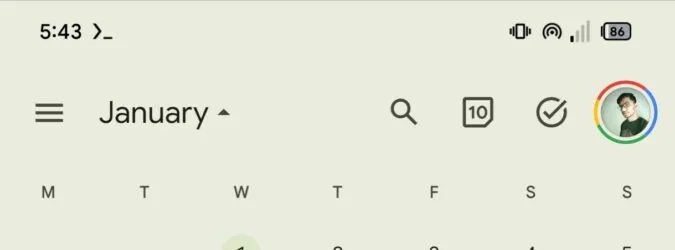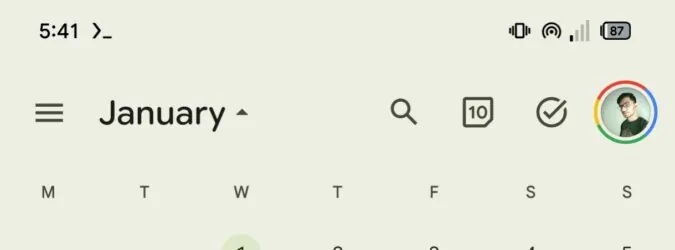
Google lavora per apportare alcune modifiche a Google Calendar, l’app calendario predefinita sui dispositivi della gamma Pixel e su altri dispositivi Android di produttori che non offrono una propria alternativa.
Nello specifico, il team di sviluppo vuole dotare l’app di una nuova impostazione per impedire la condivisione delle informazioni con altre app di calendario. Sembra, inoltre, che presto potrebbe arrivare un piccolo cambiamento allo stile dei caratteri interni all’app.
Due novità in arrivo su Google Calendar
Google Calendar è una di quelle app targate Google che non offre un programma beta pubblico, rendendo più difficile (ma non impossibile) agli insider scovare le funzionalità che verranno implementate in futuro.
Analizzando a fondo la recente versione 2025.10.0-735189449-release dell’app, il solito AssembleDebug (via AndroidAuthority) ha scovato un paio di cambiamenti a cui il team di sviluppo sta lavorando e che potrebbero vedere la luce con un futuro aggiornamento dell’app (o tramite un rilascio lato server).
Nuova impostazione per bloccare l’accesso alle informazioni del calendario
Attualmente, quando un utente concede i permessi per accedere al calendario, l’app sfrutta l’API Calendar provider di Android per accedere ai dati sincronizzati con il dispositivo da svariate app calendario.
In futuro, Google Calendar potrebbe implementare una nuova impostazione per controllare il modo con cui i contenuti vengono condivisi con altre app. L’utente potrà scegliere se condividere i dati del calendario con altre app presenti sul dispositivo (e in quel caso le app calendario di terze parti non saranno più in grado di leggere le informazioni provenienti dal calendario di Google).
Questa funzionalità potrebbe risultare utile a coloro che usano più calendari sul proprio dispositivo e che desiderano mantenere “privati” (o separati dal resto) tutti gli eventi salvati su Google Calendar.
Cambio di font all’orizzonte per alcune scritte interne all’app?
Oltre alla modifica appena discussa, il team di sviluppo potrebbe apportare anche una piccola modifica estetica a Google Calendar: nello specifico, l’app dovrebbe guadagnare il font Google Sans Flex, introdotto da Big G nel 2023 ma ancora per niente diffuso all’interno delle app targate Google.
Questo font, come potrete apprezzare dalla seguente galleria comparativa, fa comunque parte della famiglia Google Sans ma, rispetto al font usato atttualmente (prima immagine), risulta più “spesso” (quasi in grassetto) e arrotondato nelle parti terminali di ogni lettera.